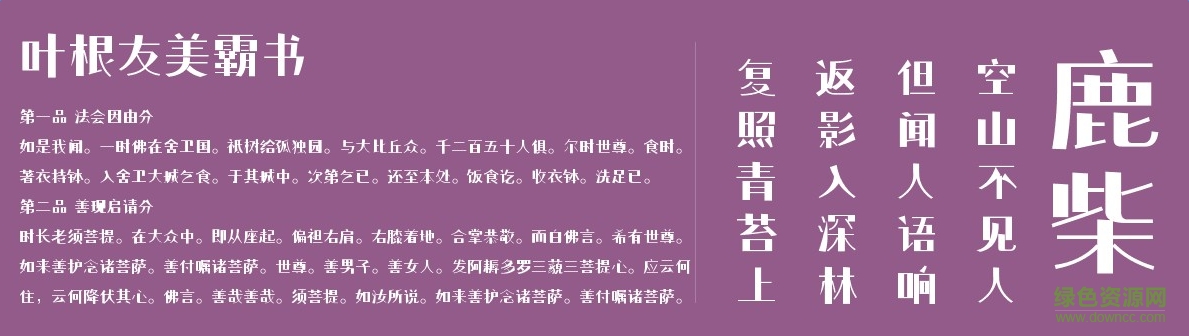
葉根友美霸書字體
葉根友美霸書是一款時尚酷炫風格字體軟件,美霸書體筆畫工整正式,十分有創(chuàng)意,整體效果比較耐看,深受廣大書法家喜愛,還有更多好看字體歡迎來綠色資源網(wǎng)下載體驗!
葉根友美霸書是一款個性鮮明,主張時尚張揚的字體,在字與筆畫的設(shè)計中,突破以往的固有模式,采用大膽創(chuàng)新的結(jié)構(gòu)演繹,使整個字體看起來別有一番霸氣韻味。